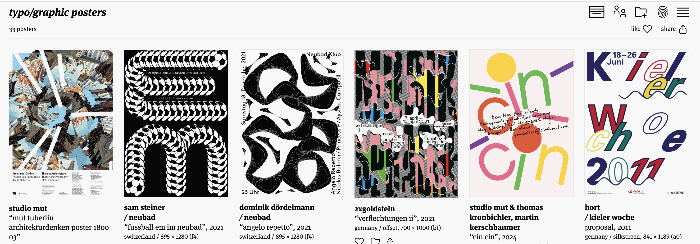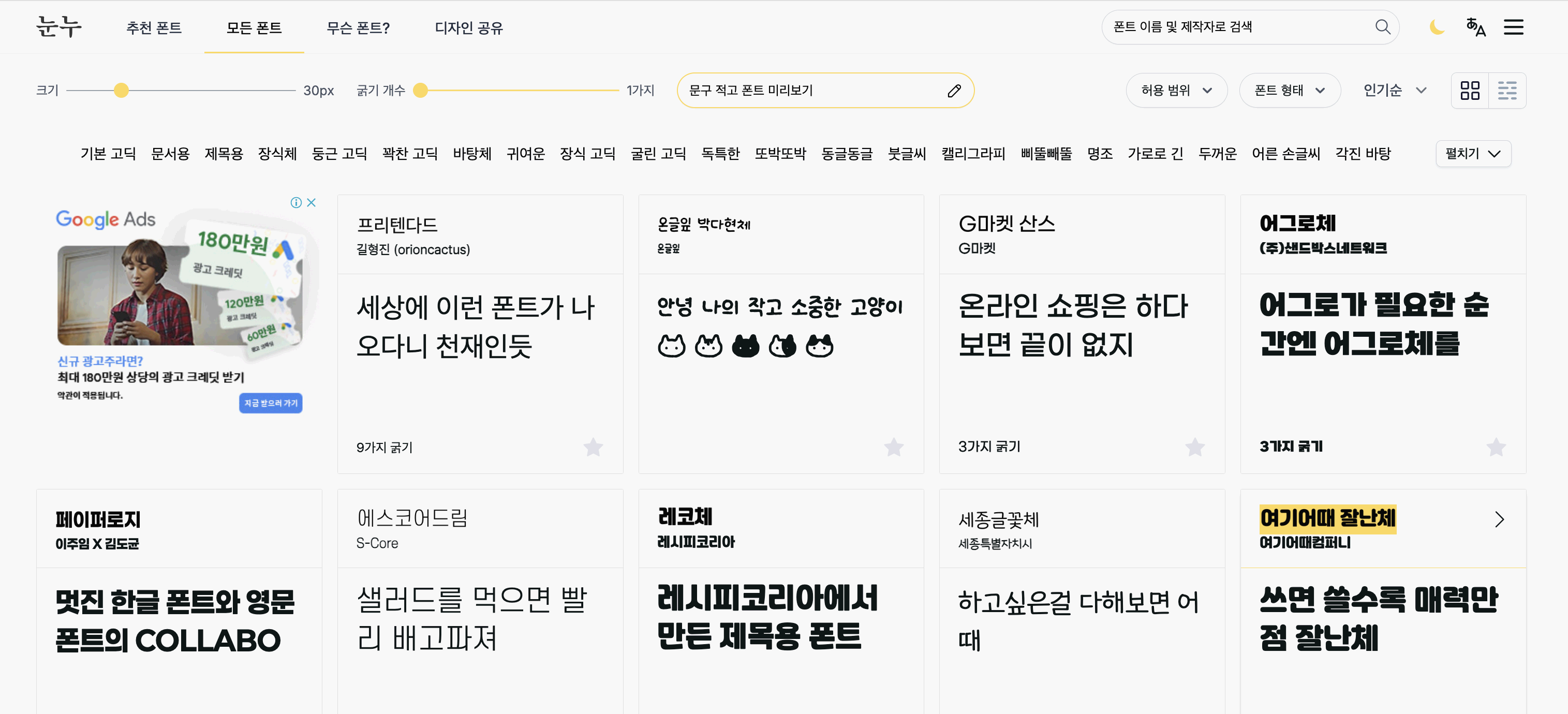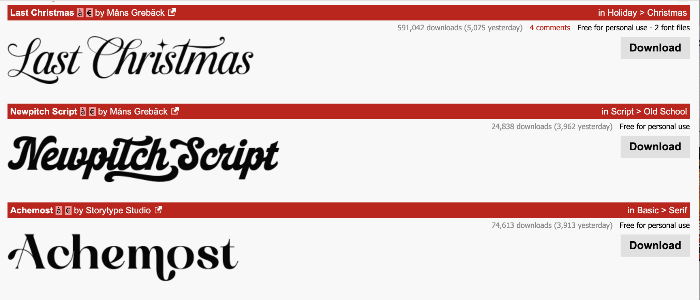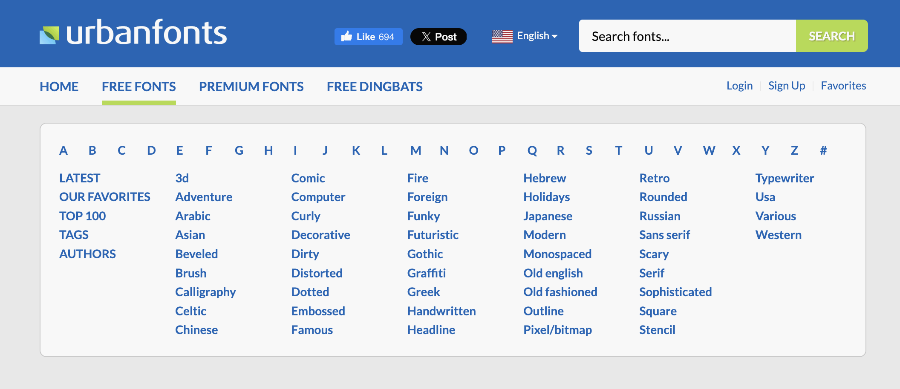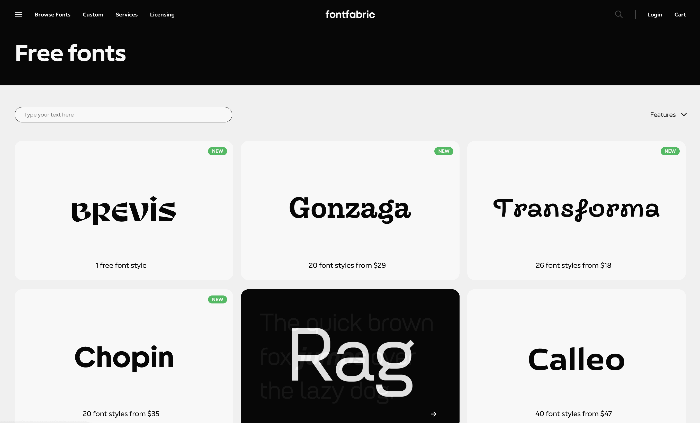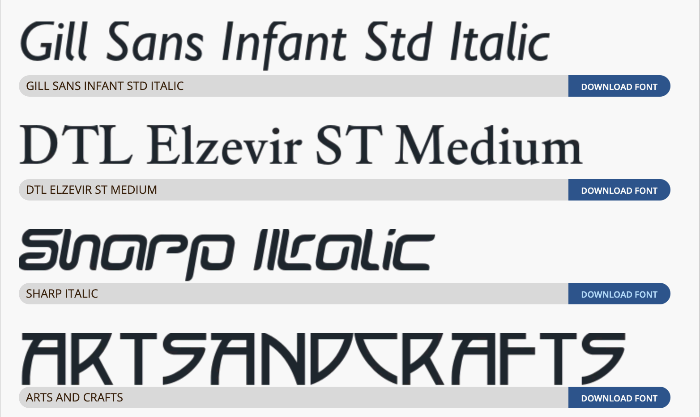
디자이너들이 자주 찾는 무료 폰트 다운로드 사이트 8곳을 소개합니다. 각 사이트는 다양한 타이포그래피 스타일과 고품질의 폰트를 제공하여, 디자인 작업을 더 쉽고 빠르게 완성할 수 있도록 도와줍니다.
1. Typographic Posters
타이포그래피 포스터를 통해 다양한 디자인 아이디어를 얻을 수 있는 사이트입니다. 타이포그래피의 예술적인 측면을 강조하여 감상할 수 있으며, 새로운 영감을 얻기 좋은 플랫폼입니다. 강추!!!
2. Typography Seoul
서울을 기반으로 한 타이포그래피 작품을 소개합니다. 한국적인 감성과 전통적인 디자인을 현대적 시각으로 풀어낸 작품들을 볼 수 있습니다. 1년에 한번씩 하는 전시에 꼭 가보시길 추천합니다.
3. Noonnu
대한민국의 웹 폰트 플랫폼으로, 한글 폰트를 상업적으로 활용 가능하며, 다양한 공개 기업 서체와 개인 창작 글꼴을 공유합니다. 무료 한글 폰트를 찾는 데 유용합니다. 너무나도 유명한 사이트입니다.
4. Dafont
무료 영어 폰트의 방대한 라이브러리를 제공하며, 다양한 스타일과 카테고리에서 폰트를 쉽게 찾아 다운로드할 수 있는 플랫폼입니다. 매우 직관적이고 다양한 선택지가 있습니다. 영어는 다폰트에서 해결!
5. Urban Fonts
트렌디하고 현대적인 스타일의 무료 영어 폰트를 제공합니다. 웹 및 프린트 디자인에 적합한 폰트들이 많아 다양한 디자인 작업에 유용합니다.
6. MyFonts
다양한 폰트 및 글꼴 관련 정보와 뉴스레터를 제공하는 사이트로, 최신 폰트 출시와 트렌드에 대한 정보를 얻을 수 있습니다. 유료 폰트도 다수 포함되어 있습니다.
7. FontFabric
특장점: 폰트 디자인 스튜디오에서 제공하는 다양한 무료 영어 폰트들을 다운로드할 수 있는 사이트입니다. 세련된 스타일의 폰트들이 많고, 상업적으로도 사용 가능한 폰트들이 제공됩니다.
8. FontYukle
다양한 언어와 스타일의 무료 폰트를 제공하며, 검색 기능이 간편하여 사용자가 원하는 폰트를 쉽게 찾을 수 있습니다. 다양한 폰트와 언어를 지원하여 글로벌 프로젝트에도 유용합니다.
디자인에서 폰트는 단순한 글자가 아니라, 전체적인 분위기와 메시지를 전달하는 중요한 요소입니다. 다양한 무료 폰트 다운로드 사이트를 활용하면, 디자인 작업에 필요한 폰트를 쉽게 찾고 효율적으로 사용할 수 있습니다. 각 사이트의 특성을 잘 이해하고, 자신만의 디자인에 적합한 폰트를 선택해 보세요. 이들 사이트를 즐겨찾기 하여 앞으로의 작업을 더 빠르고, 창의적으로 완성할 수 있습니다. 친절한 고고씨였습니다. Go Go!